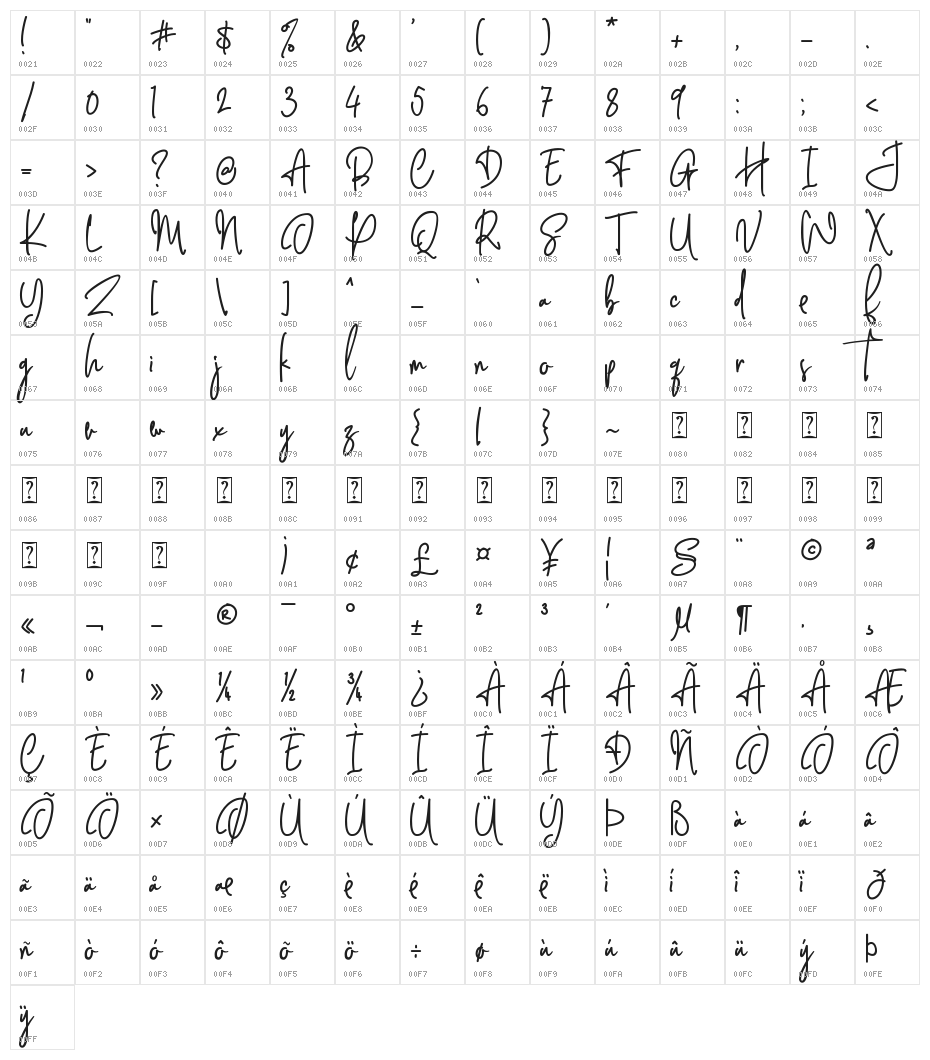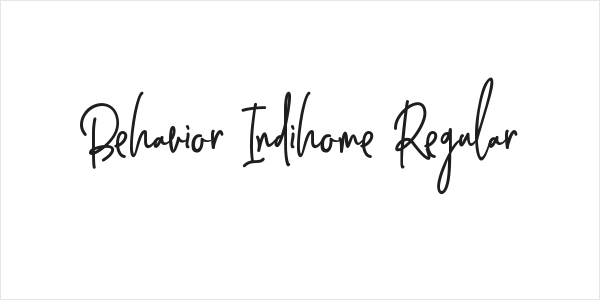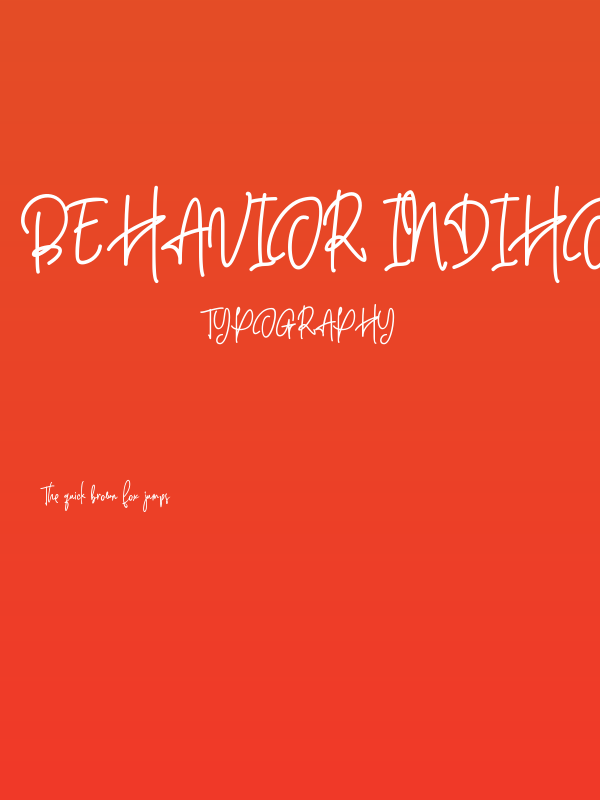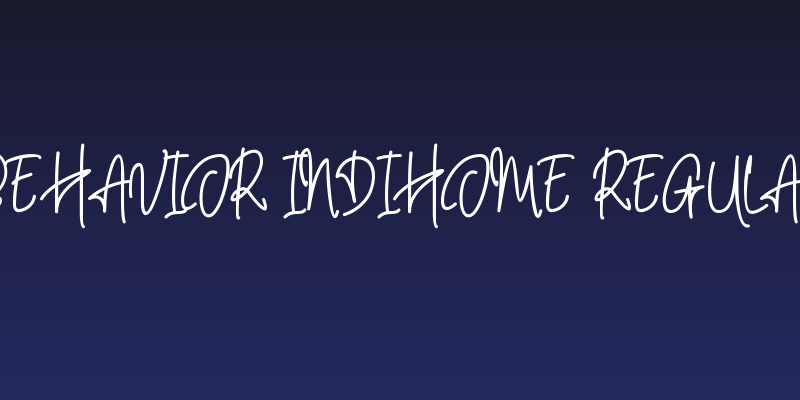
Behavior Indihome Regular Font
| Anwendungsfall | Logos, Headlines, Creative projects |
| Vorgeschlagene Projekte | Ideal for greeting cards, personal branding, invitations, and creative projects that benefit from a personal and artistic touch. |